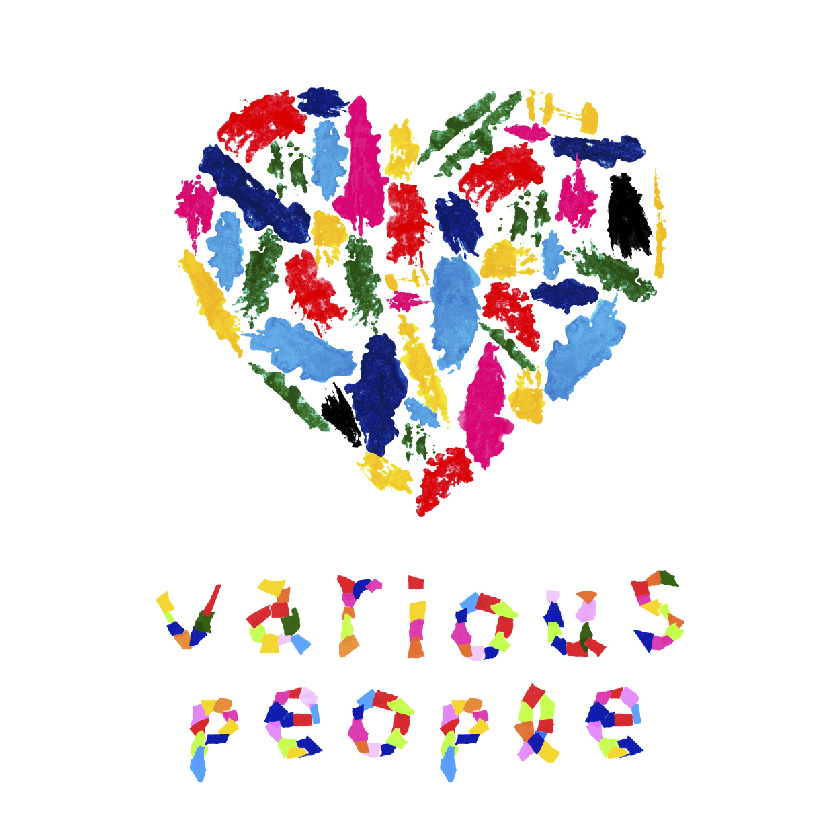
various people
みんな違ってみんな良い
ポスカを押したらインクがたくさん出てきてしまって、困りましたが、伸ばしたりして、楽しんでやっていました。(澤田和弘)(澤田和弘)
偶然か、必然なのかこのデザインを愛してください(伊藤小雪)(伊藤小雪)
実際に描いていたものではなく、描いたものから予想外にできた原画を使うとは思っていませんでした。色とりどりの部分が、ストライドの個性を出しているように見えます。(ストライドクラブ)(ストライドクラブ)